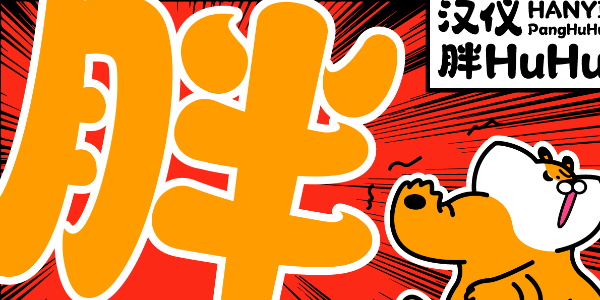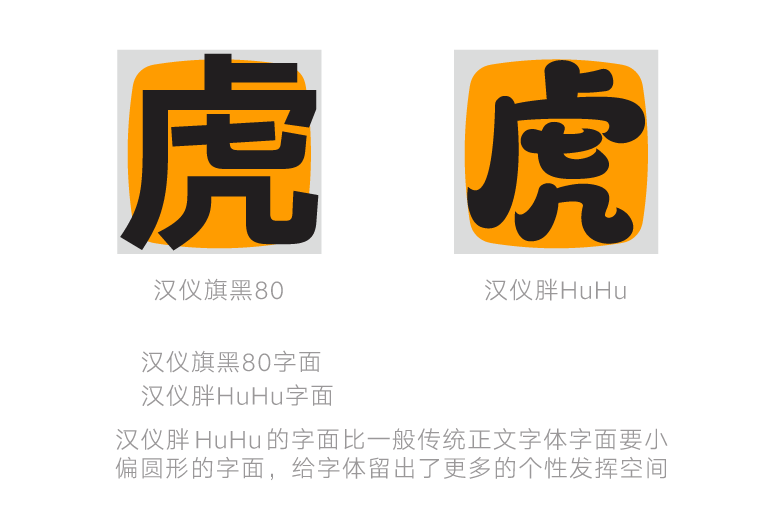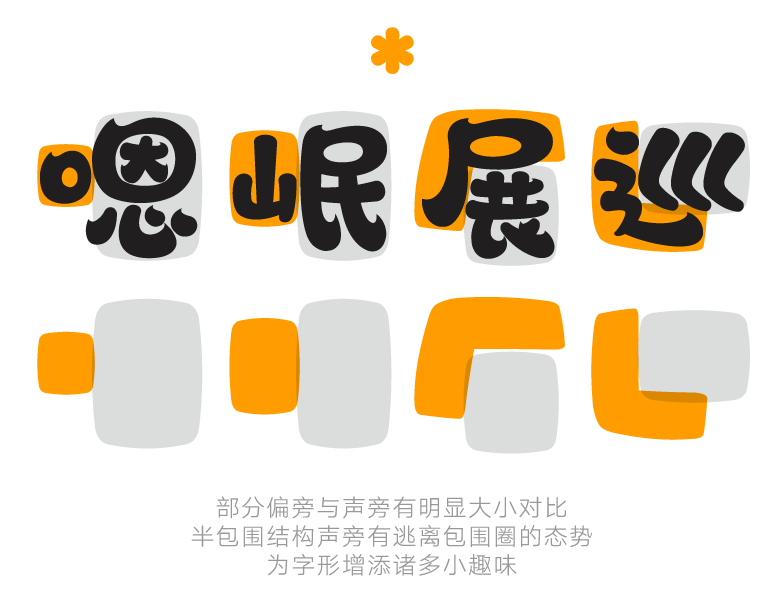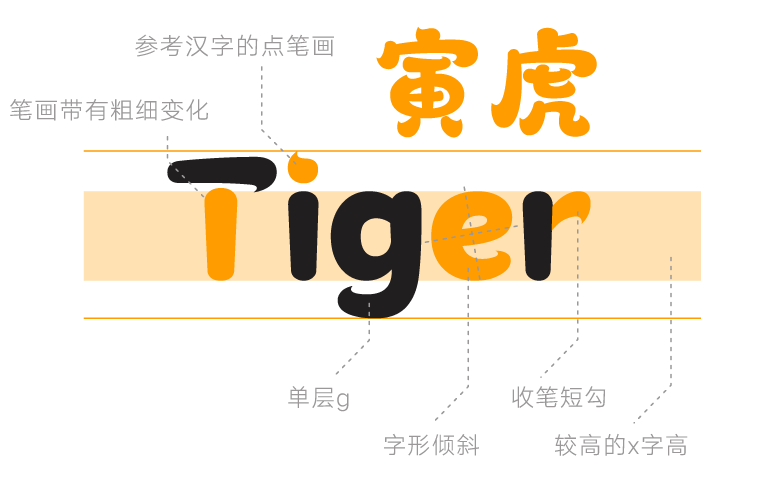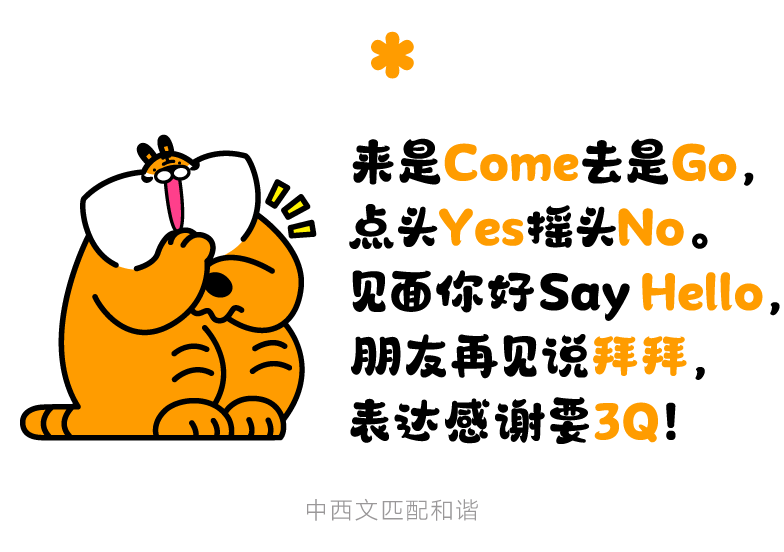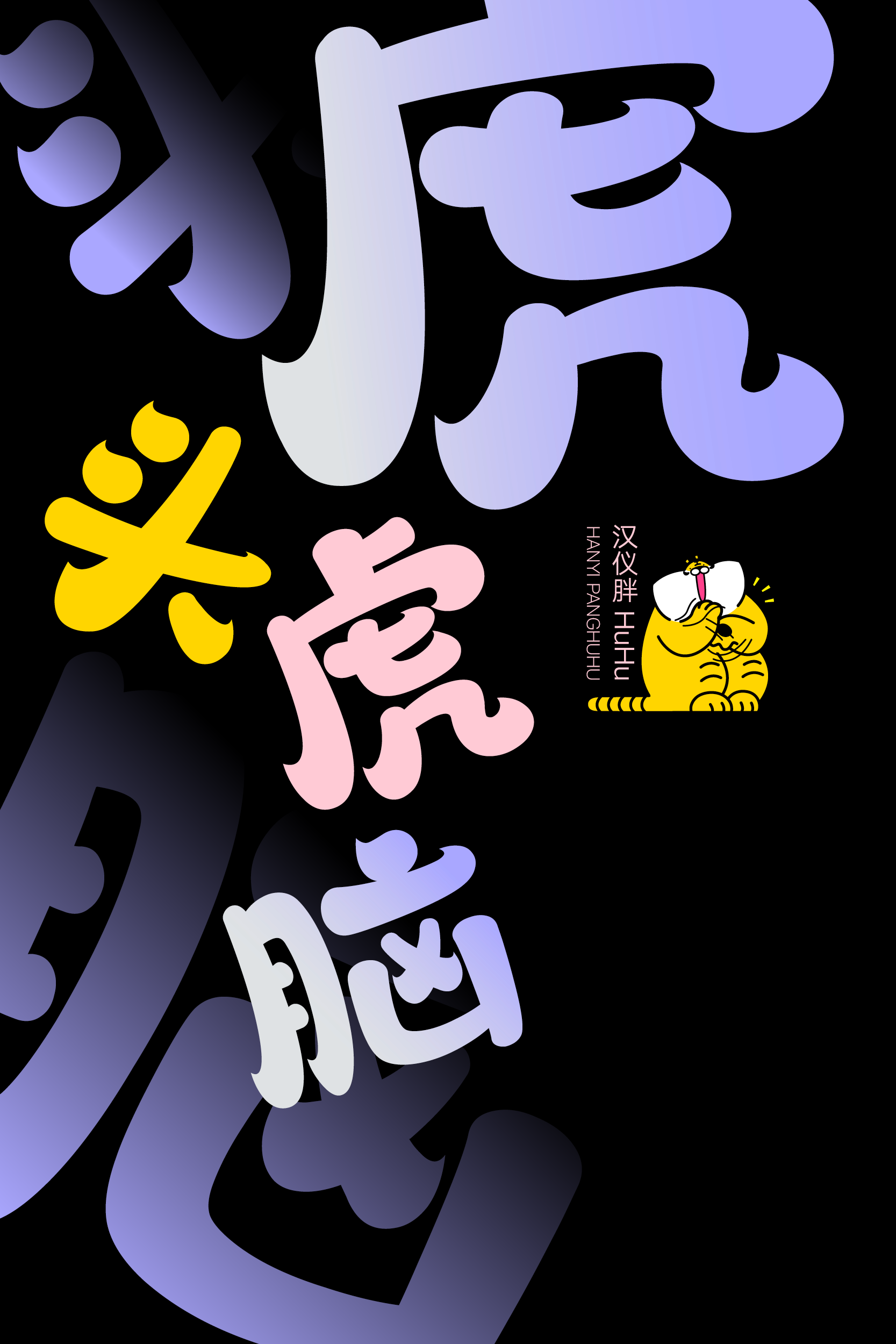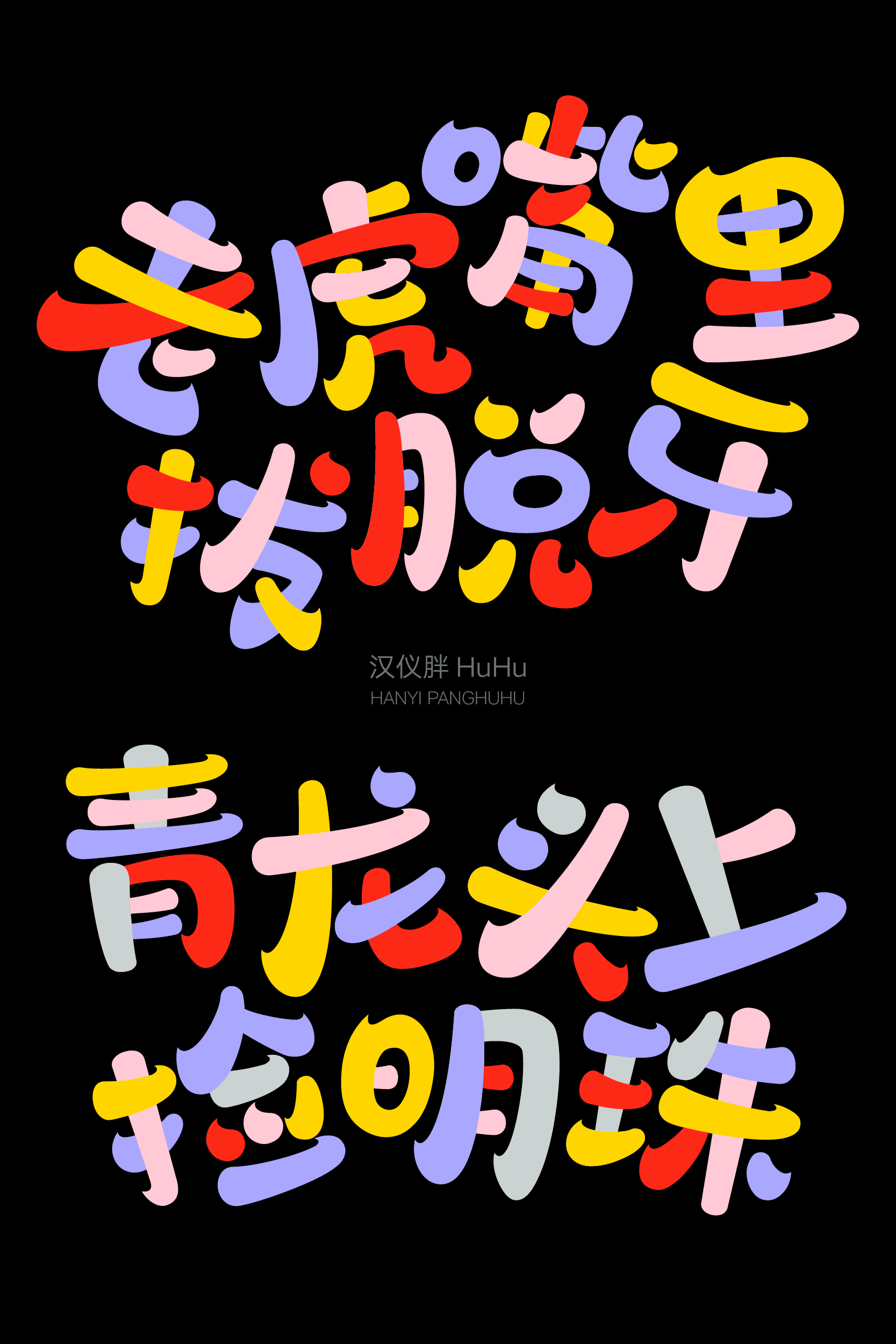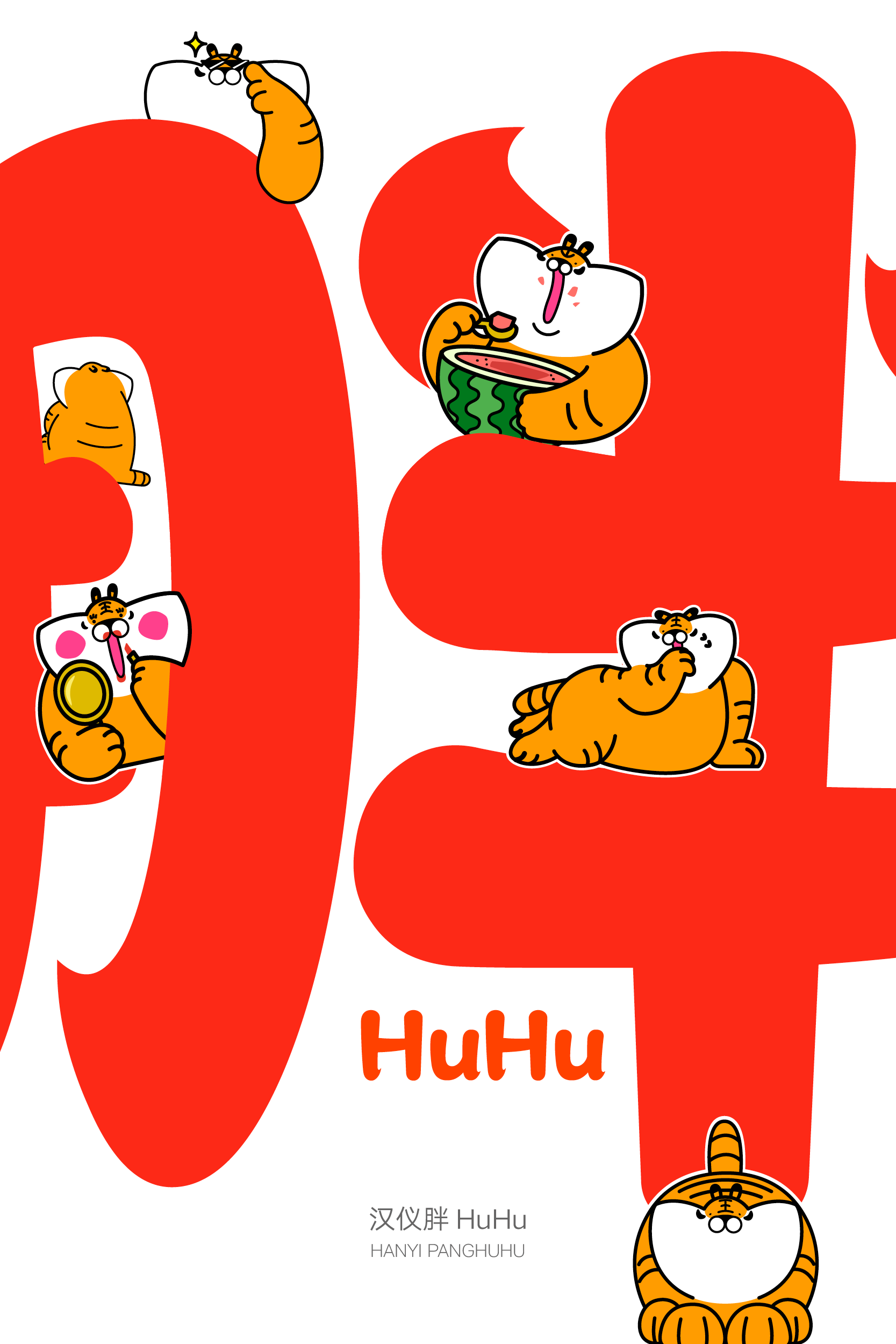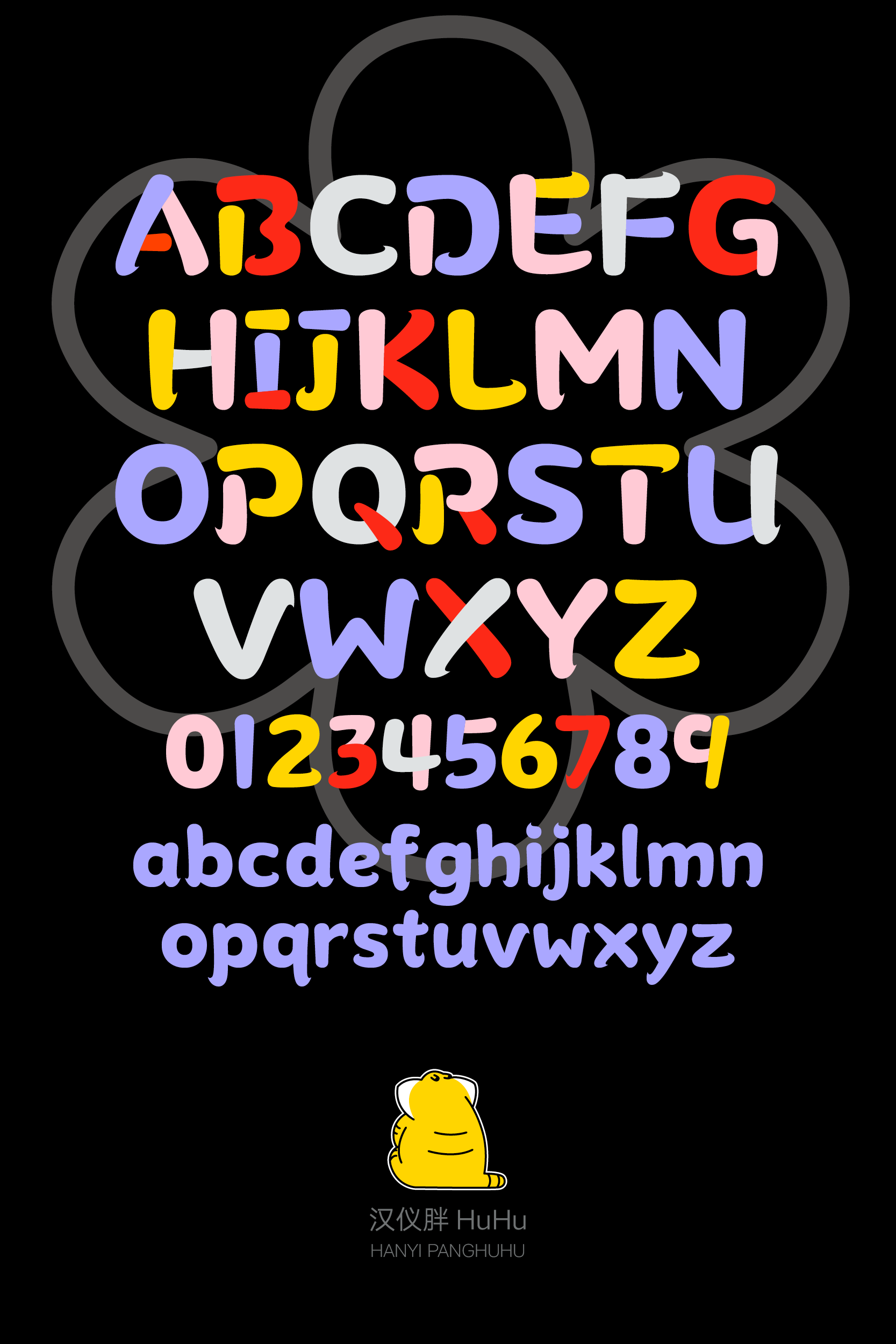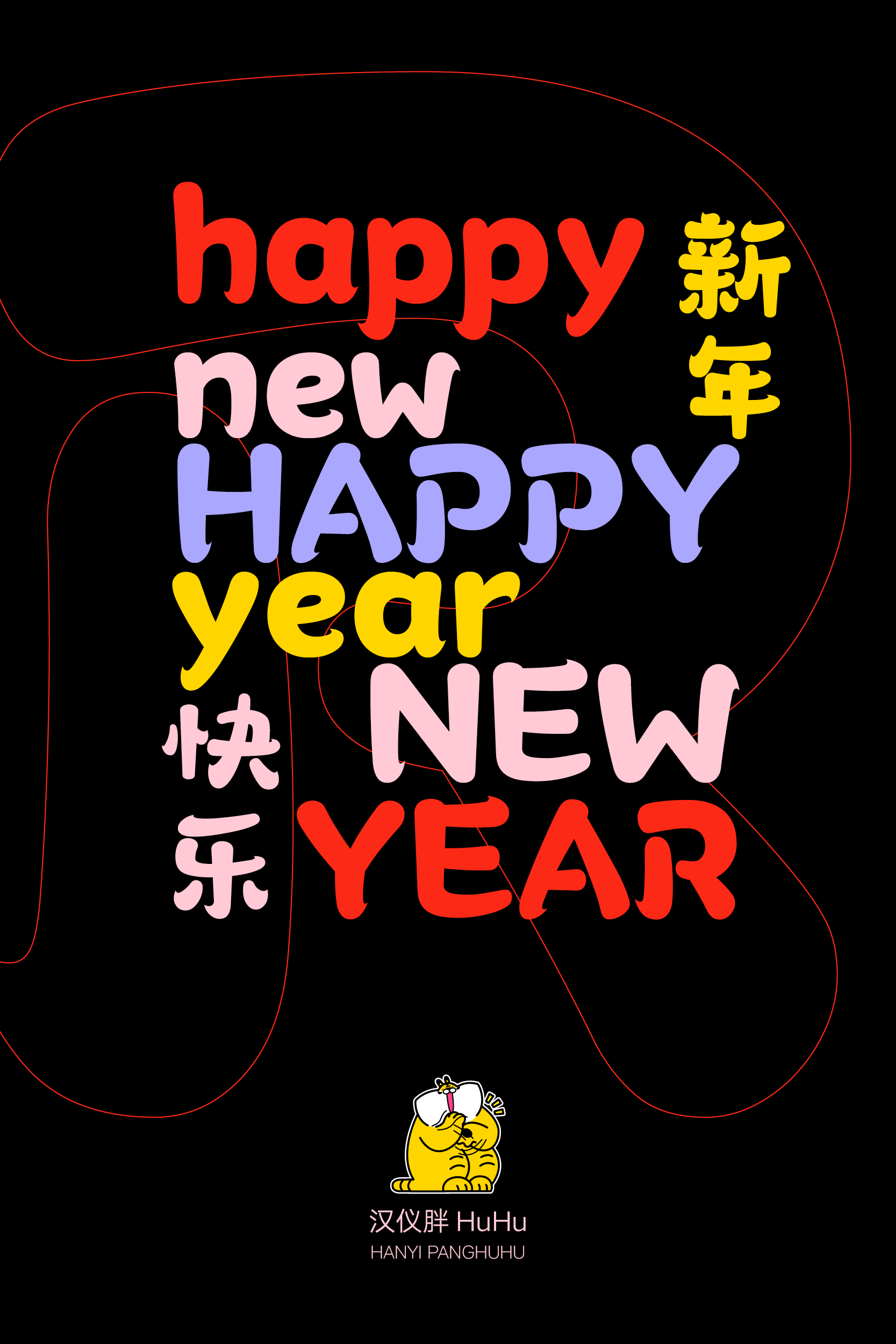
这个字体有点胖HuHu~
汉仪胖HuHu是汉仪旗下“永字社”工作室设计的一款胖乎乎的创意设计字体。这款字体有着油光水滑的笔画设计、鼓鼓囊囊的字形轮廓,带来可爱灵动、祥和美好的气息,给人一种生龙活虎、虎头虎脑、虎虎生威的印象。因此这款字适合用在儿童绘本、餐饮娱乐、玩具周边等需要传递喜庆、欢乐、童真、可爱气氛的场合。
汉仪胖HuHu有着胖乎乎的结构设计,整个字面向四周微鼓,看起来更加圆润。
这款字体有着晃悠悠的造型设计,结构灵活,左右摇摆,俏皮可爱。该字体字面稍小,并且会随着每个字的组合结构不同而产生宽窄高低的变化,赋予每个字形充足的个性发挥空间。
汉仪胖HuHu有着圆鼓鼓的起笔与毛烘烘的收笔,既展现出笔画的运笔顺序,又增强了字形的装饰感,增添俏皮的印象。
这款字体有着油光光的曲线轮廓和肥嘟嘟的笔画粗细设定,有助于提高文本内容的亲和力。
该字体不同位置的笔画有着不同的形态,为字形增添诸多趣味。
汉仪胖HuHu的西文部分参照了中文的笔画设计,保留了中文圆滑、肥嫩、摇摆的造型特征。中西文混排情况下节奏感良好,匹配和谐。